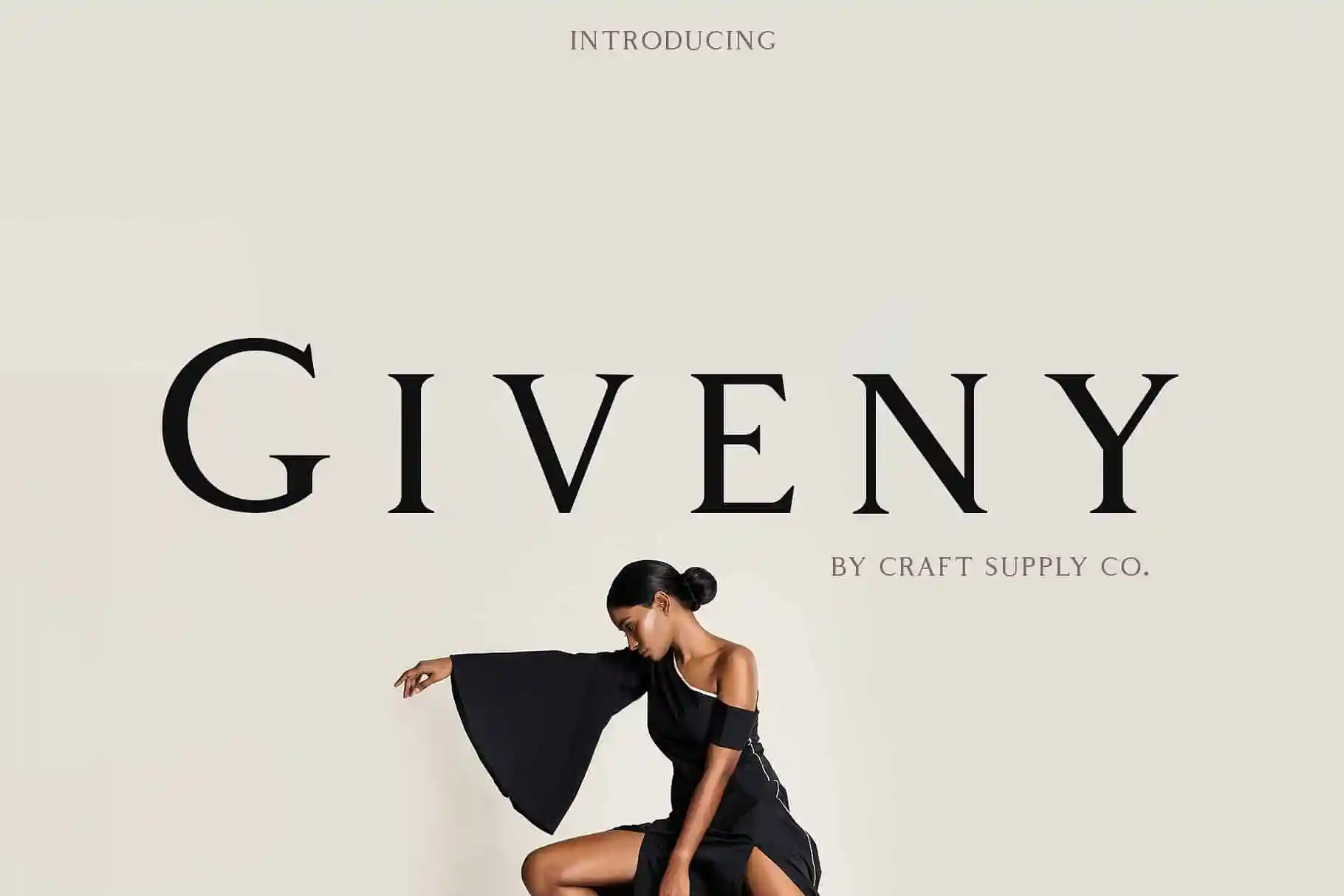
Giveny Serif Font – Fonte Grátis
Giveny Serif Font
Esta é uma fonte serif contemporânea que transmite formas geométricas simples combinadas com bases tipográficas fortes. É perfeita para todos os seus projetos de design. Introduzimos a fonte Giveny. A fonte Giveny Serif é uma fonte serif cujo design nos remete ao estilo das serifas em transição. As características distintivas da fonte Giveny Serif são o contraste relativamente baixo entre as linhas, formas ligeiramente quadradas dos caracteres redondos e a natureza empresarial destacada. A fonte Giveny Serif foi criada de zero com uma lógica estrutural própria: uma fusão de geometria pura e equilíbrio óptico. Combinando vários estilos, a fonte Giveny Serif é ideal para logotipos, cartões de visitas, citações, postais, identidade visual, cartões de papelaria, cabeçalhos de design, cabeceiras de blog e citações artísticas. Esta fonte serif moderna e elegante oferece uma versatilidade que vai do logotipo à cabeceira de blog. Suas formas leves e equilibradas a tornam um recurso valioso para designers que estão em busca de uma transição suave entre o tradicional e o contemporâneo, sem perder seu caráter forte e robusto. Perfecta tanto para aplicativos profissionais quanto para uso pessoal.